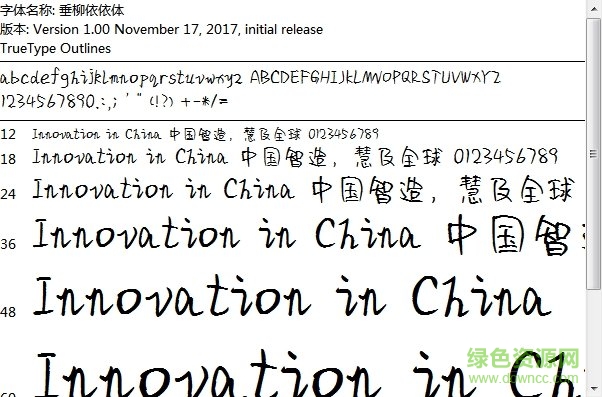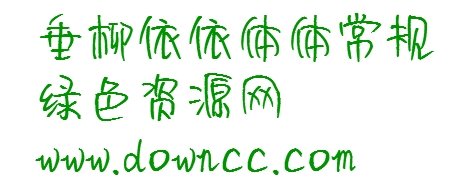
垂柳依依體字體
垂柳依依體ttf是一款清秀婉約的手寫(xiě)字體,有著柔和雅致的筆觸,筆畫(huà)之間盡情柳枝隨風(fēng)纏綿的恣意清揚(yáng)之態(tài),給人十分活躍的內(nèi)心萌動(dòng)體驗(yàn),綠色資源網(wǎng)今日推薦!
垂柳依依字體介紹
昔我往矣,楊柳依依。
今我來(lái)思,雨雪霏霏。
垂柳依依體 常規(guī)
古人送行,折柳相贈(zèng),表示依依惜別。比喻依依不舍的惜別之情。
垂柳依依體是一款筆畫(huà)圓潤(rùn)、親切溫柔的女生字體,藝術(shù)效果十分出色,讓人在閱讀中也有著寧?kù)o享受,可用于海報(bào)創(chuàng)意、藝術(shù)設(shè)計(jì)、文字印刷、排版設(shè)計(jì)等場(chǎng)合。